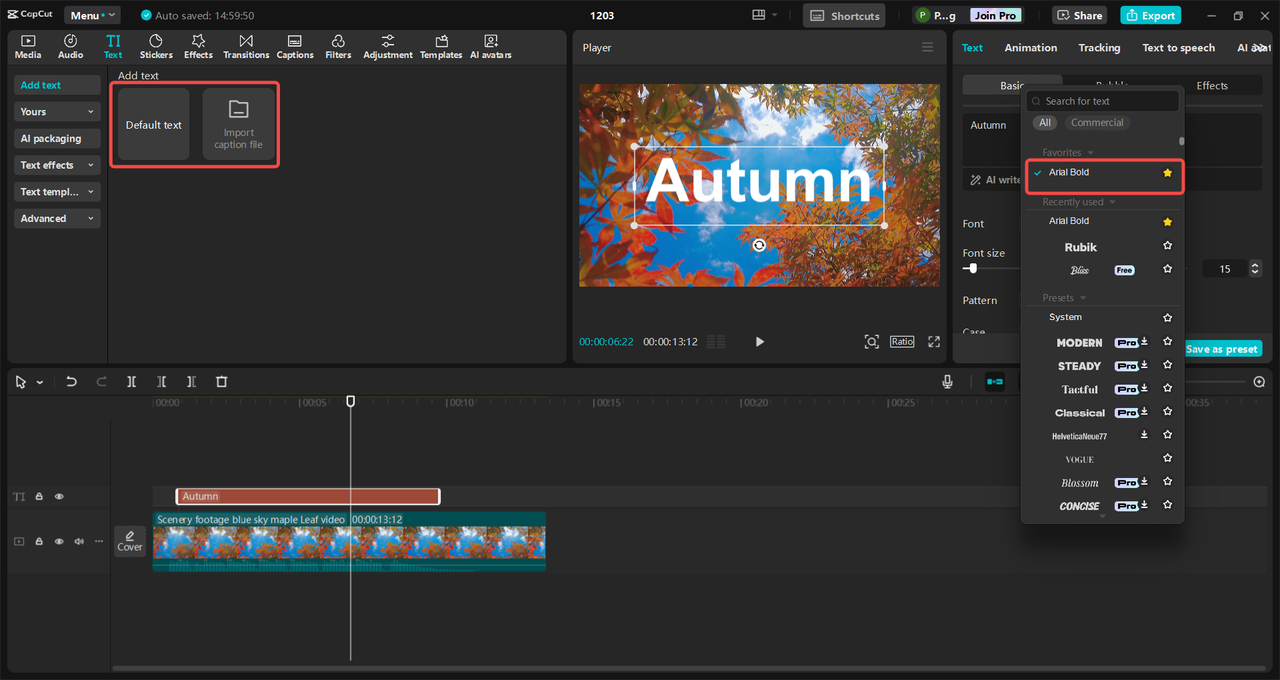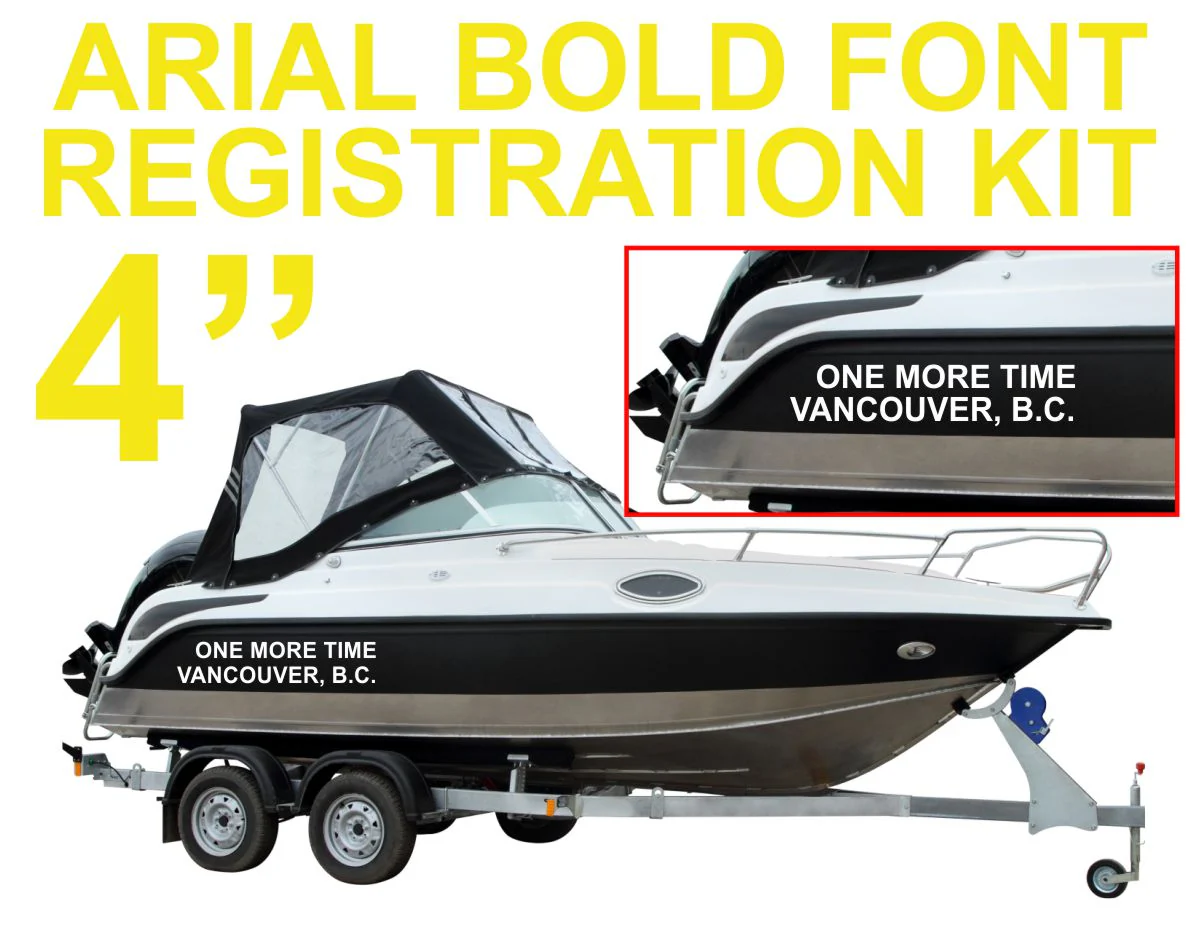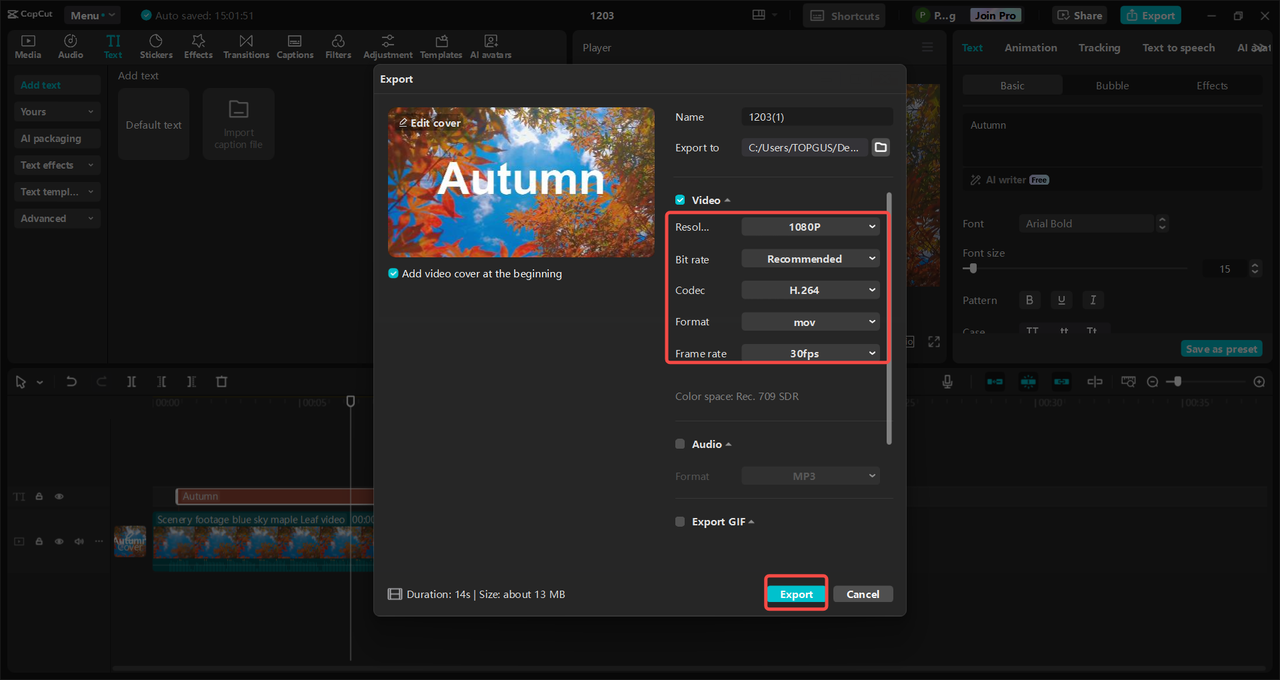
Apakah fon Arial Bold
Arial Bold ialah muka taip sans-serif serba guna yang direka untuk kejelasan dan kebolehbacaan. Ia menampilkan sapuan yang lebih tebal, menjadikannya sesuai untuk tajuk utama dan penekanan dalam teks. Sebagai sebahagian daripada keluarga fon Arial, ia mengekalkan gaya neutral lagi profesional muka taip Arial. Ia digunakan secara meluas dalam reka bentuk digital dan cetakan untuk keseimbangan antara kesederhanaan dan impak.
1. Apakah yang menjadikan fon Arial Nova Bold berbeza daripada Arial Bold tradisional?
Arial Nova Bold berbeza daripada Arial Bold tradisional dalam reka bentuk yang lebih halus dan bentuk huruf yang halus. Walaupun kedua-dua fon mengekalkan struktur teras yang serupa, Arial Nova Bold mempunyai rupa yang lebih moden dan digilap, menjadikannya lebih sesuai untuk pelbagai reka bentuk digital dan cetakan. Menggabungkan alatan seperti CapCut boleh meningkatkan lagi reka bentuk anda apabila menambahkan teks Tebal pada projek video.